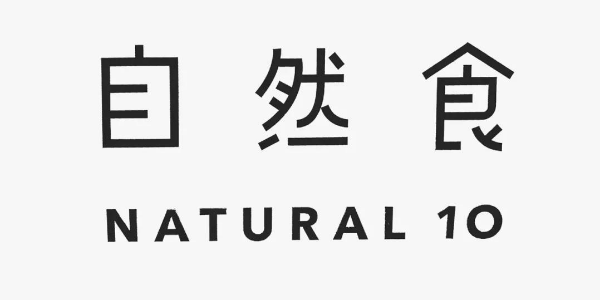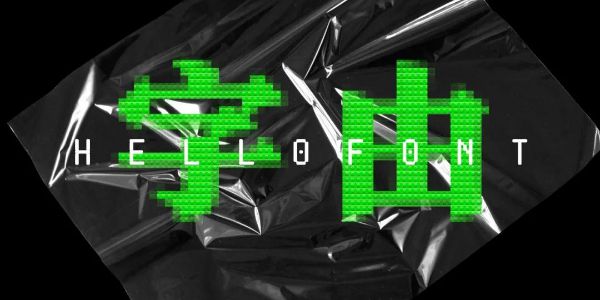
PPT文字排版技巧,高大上的PPT文字排版技巧分享
你们可能不知道那种“能把PPT文字排版得好看的人”是什么概念,我们一般只会用两个字来形容这种人——P怪。
我经常说一句话,当年贾某人能靠PPT忽悠到几个亿,我木某人用一篇教程忽悠到大家的32个赞,不是问题。
想把PPT文字排版得好看,其实你只需记住一个原则——让PPT里的文字看起来更像图形即可。
接下来,本P怪将用4个方法向你展示具体该如何让文字看起来更像图形:
为文字设置字效
不要让文字变成方块
既是文字又是图案的文字云
让文字之间形成对比
▎为文字设置字效
我曾写过两篇关于PPT文字设计的文章,在这两篇文章里我一共介绍了十几种字效:
很多人可能会觉得我做这些PPT只是在炫技,因为“并不实用”。
对此我只能说:别误会,虽然我真的是在炫技,但你千万不能说它们不实用,因为下一秒你就会说真香了…
不信的话你对比一下下面两个案例,你会发现比起单纯的文字,使用了字效的文字看起来会更美观,这就是把文字图形化以后的力量:
所以,今后再遇到一页PPT中只有几个简单的文字时,你就可以为这些文字设置一些字效,这样PPT看起来就不会太单调。
▎不要让文字变成方块
很多人都觉得同样的排版,把英文换成中文就会变丑,或者说看起来怪怪的。
其实并不是中文天生比英文丑,而是由很多复杂的原因造成的。
其中一个重要原因就是:英文的每个单词的长度都不一样,所以每个单词或每条句子之间在长度上就有一种对比的美感。
而由于中文的每个文字的宽度都是一样的,所以每行句子的长度都是一致的,导致大段大段的文字起来看着就像一块块方块,显得很呆板。
想要改善这种呆板的感觉也很简单,适当地为文字断句以及分段即可,这样不仅能直接消除方块的呆滞感,还能减轻读者的阅读负担:
所以,今后如果要排版大段大段的中文时,记得及时为文字断句以及分段,这样版面看起来才不会太呆板。
▎既是文字又是图案的“文字云”
前面介绍的两个技巧,都是为了让文字看起来更像图形,但本质上它们还是文字。
而下面要介绍的这个文字云技巧,则是丧心病狂地直接把文字变成了图形,拐了180度的大弯还不带刹车的那种直接:
当你的PPT中只有非常非常少的文字时,你就可以利用文字云,没有素材也能给自己创造素材:
这种文字云效果是怎么做的?很简单,借助一个叫做【WordArt】的网站即可。
1)打开网页wordart.com,点击【立即创建/creat】:
然后你就会看到这个页面:
2)在左侧的面板中你可以设置各个参数:
3)网站的具体使用方法如下:
a、在【话/word】中输入你的文字,并且分别设置好每个词的颜色:
b、在【形状/shapes】中选择文字的形状,你可以选择系统自带的形状,也可以点击【添加图片/add image】自己插入形状(这个形状必须为PNG格式的图片):
我这里就是插入了一张在PPT中制作的图片:
这种图片的制作方法也很简单,你只需要插入一个文本框然后输入文字,接着右击文本框,将文字另存为图片即可。
c、由于这个网站是外网,所以它不支持中文字体,因此我们需要点击【字体/fonts】-【添加字体/add font】来添加中文的字体文件:
字体文件上传完毕以后,大家需要回到【话/word】中,把你的中文单词设置为我们刚刚上传的那个字体:
d、点击【样式】-【背景颜色】,并滑动按钮至最左侧,再点击【应用/apply】,即可将背景设置为透明背景:
e、点击【想象/visulize】,此时你就能预览最终的效果了:
f、如果不需要修改了,你就可以点击【下载/download】,然后选择一种你想要的图片格式来下载即可:
最终把生成的图片放到PPT里,一切就大功告成了!
▎让文字之间形成对比
虽然这个文字对比法我已经讲过N次了…但考虑到人类就是复读机的本质,我就再重复一遍好了…
所谓的文字对比,就是指——排版文字时,你应该尽可能让文字之间形成对比,这种对比可以是颜色、字体、字号、甚至是笔画粗细的对比都行。
我举几个例子。
1)案例一:下面这页PPT里的文字,用到了字体、字号、文字长度、中英文对比。
2)案例二:下面这页PPT里的文字,用到了字号、字色、文字长度、笔画粗细对比。
3)案例三:下面这页PPT里的文字,用到了字色、字体、字号、文字长度、笔画粗细对比。
现在能理解什么是文字对比了吧,在平面设计中,很多元素之间就是因为有了对比,所以才碰撞出了美感。
最后,我们来总结一下在PPT中文字到底该怎么排版才好看:
为文字设置字效,能让文字看起来更像图形;
适当为文字断句、分段,能让大段文字不显得呆滞;
使用文字云,直接把文字变成图形;
让文字之间形成对比,可以营造对比的美感。